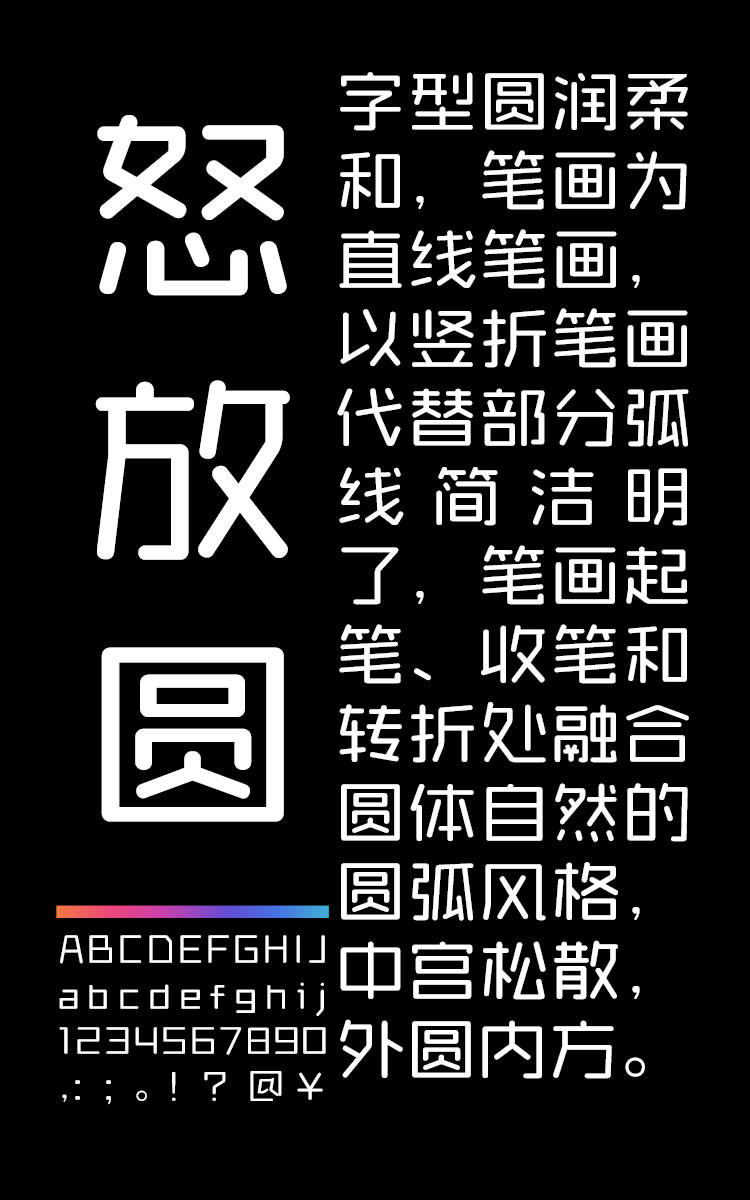
锐字锐线怒放圆 常规
锐字锐线怒放圆 常规,这款字体结构工整、笔画清晰,兼顾美观与易读性,适用于标题、正文、海报、包装、LOGO 等多种场景。字形优雅稳定,风格百搭耐看,适配日常排版与创意设计,让文字呈现更舒适、更具质感。锐字锐线怒放圆 常规一笔一画,皆是细节,以均衡的比例、流畅的线条打造舒适视觉体验,字形端正大气,风格简约现代。无论是商业设计、品牌宣传还是日常排版,都能轻松驾驭,让文字更有格调与力量。锐字锐线怒放圆 常规字体下载。
锐字锐线怒放圆 常规字体介绍
锐字锐线怒放圆 常规字样展示
字型圆润柔和,笔画为直线笔画,以竖折笔画代替部分弧线简洁明了,笔画起笔、收笔和转折处融合圆体自然的圆弧风格,中宫松散,外圆内方。此款字体是具有3款字重的家族字体,适用标题和正文,具有良好的视觉表现与阅读体验,可以适配多种风格与样式的排版。